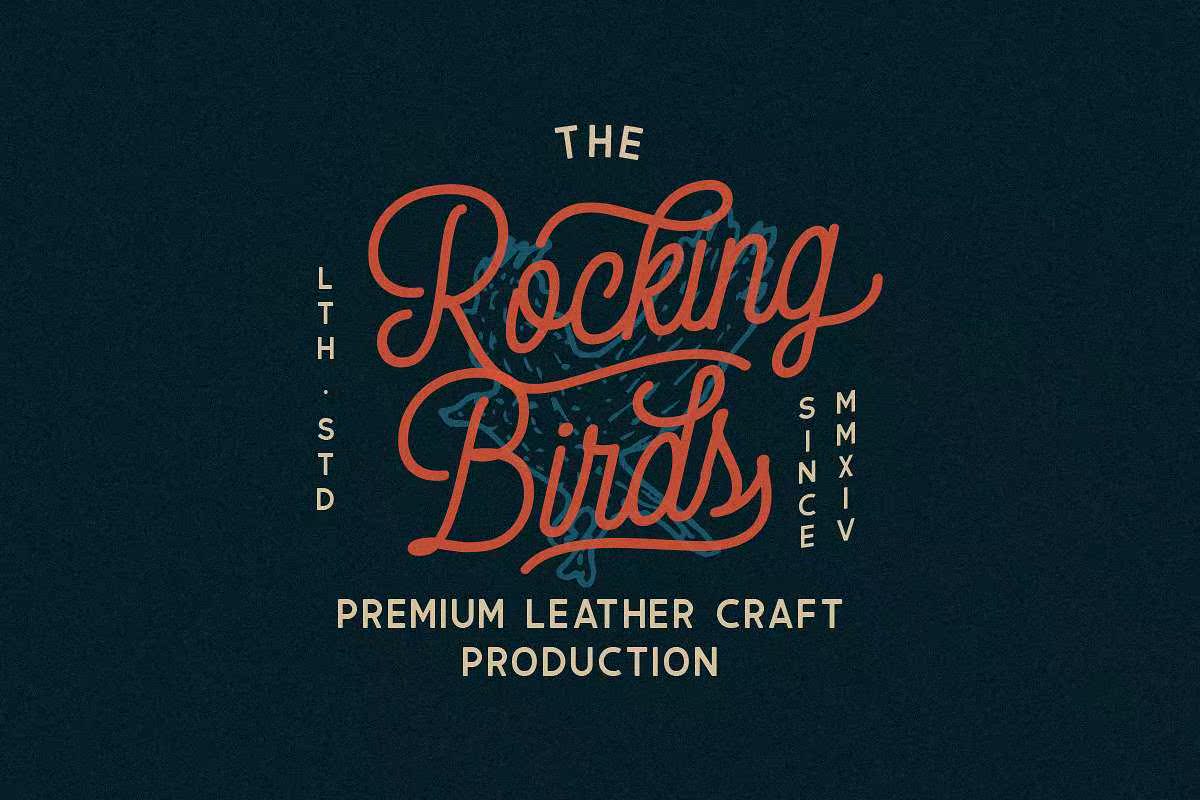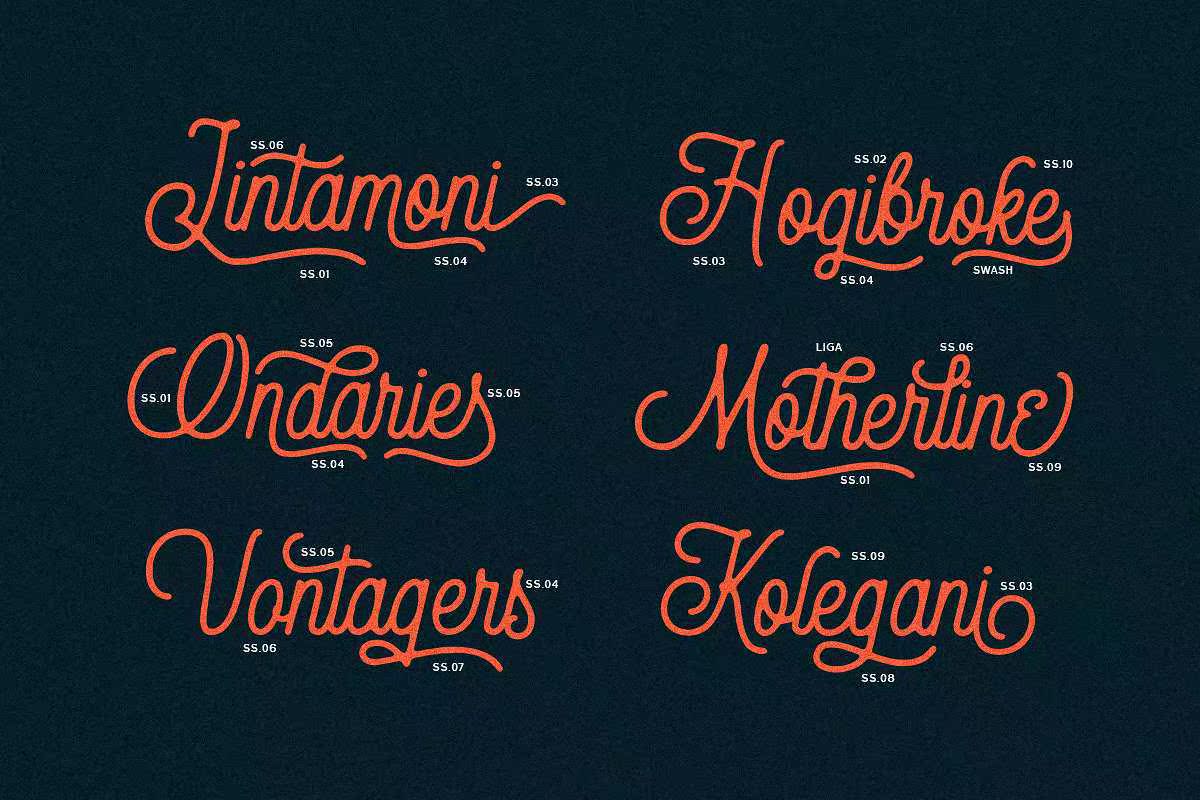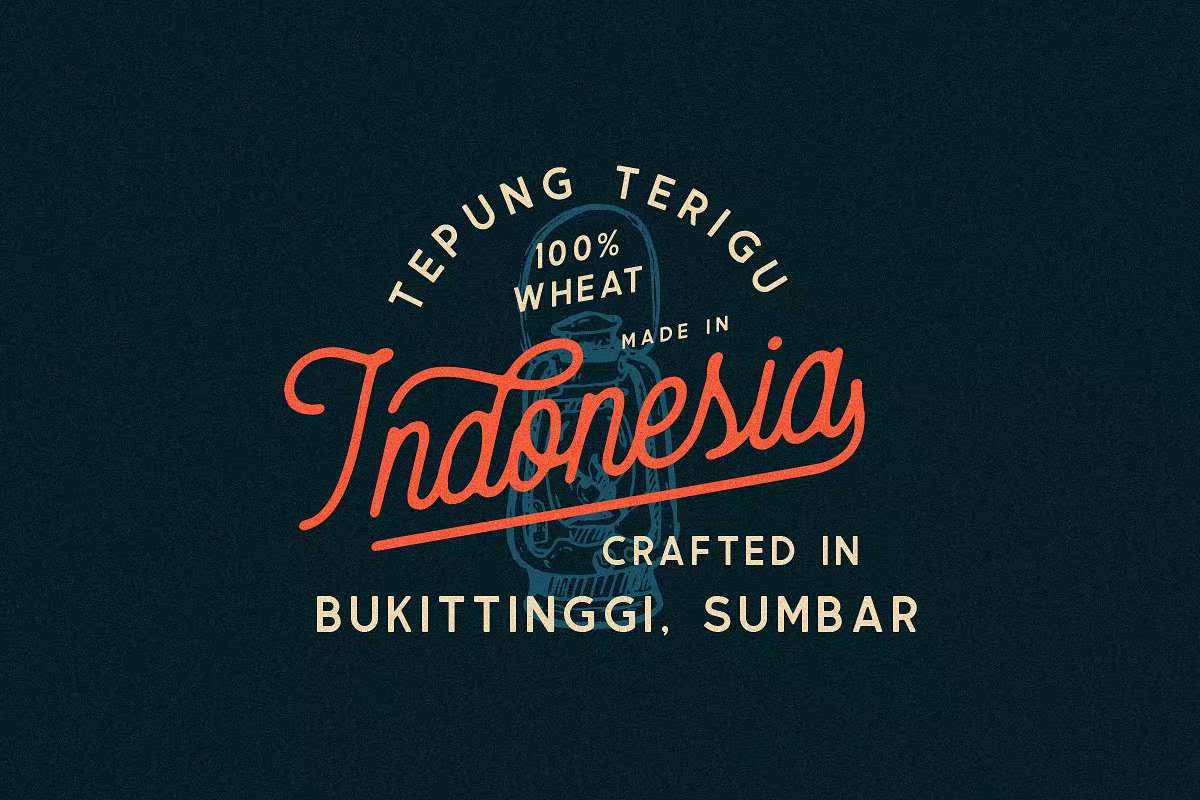
介绍,第三个。A和mandetypeface,使用单线和sans。您可以获得一个庞大的、可与Front完美结合的和DrawnilLustmentInvestor格式集合。它包括100++对象,如广告、自然、动物、海滩、海洋、度假等。此字体适用于您的时装设计、徽标/品牌、签名、标题、文字引用,等等。它还包括大写、小写、标点符号、符号和数字、文体设置交替、连字等,支持多语言。介绍、第三人称、单字和sans的mandetypefaces。您可以使用大量的HandDrawnilLustionInvestor集合,这些集合可以与字体完美结合。它符合100++客观习惯,如广告、自然、,动物、海滩、海洋、度假等。此字体适用于EUSEDASTSHIRT设计、徽标/品牌、签名、标题、字母引号等。它还包括大写、小写、标点符号、符号和数字、文体设置替换、连字等,支持多种语言。